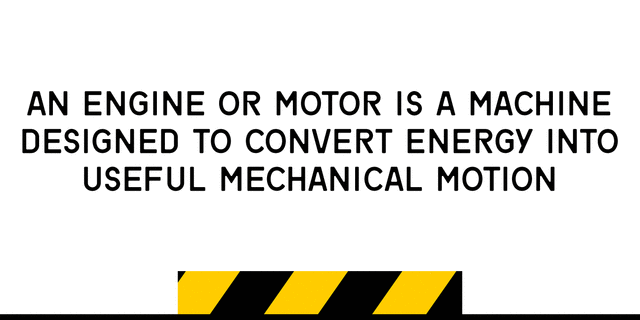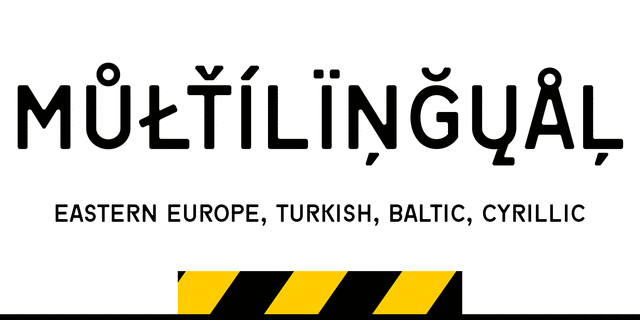
Мотор — акцидентный щрифт, сделан по мотивам букв автомобильных номерных знаков, принятых в России. Разработан Сергеем Ткаченко в 2014 году.
Ассоциации c начертанием Motor 4F BoldКачества и характер:
важный, тяжелый, точный, ровный, убедительный, прямоугольный, стабильный, статичный, простой, нейтральный, прямой, современный, глобализированный, глобалистичный, монотонный, логичный, прагматичный, практичный, твердый, лаконичный, доступный, серьезный, железный, стальной, надежный, уверенный, сильный, устойчивый, автоматический, искусственный, холодный, машинный, инженерный, индустриальный, техногенный, военный, армейский, стандартный, городской, грубый, рабочий, мотивирующий, суровый, железнодорожный
промышленность, техника, станок, код, тара, электростанция, энергетика, армия, оружие, машиностроение, завод, чертеж, конструктор, инженер, автоматика, автомобиль, мотор, ГОСТ, пресс, город, навигация, наука, ремонт, шахта, шахтер, каска, униформа, вагон, авиация, самолет, грузовик, внедорожник, страйкбол, стройка, строительство, обувь, кирпич, дальнобойщик, сталевар, двигатель, технологии, железная дорога, топливо, шоу, телевидение, рабочий, доставка, нефть Стилистика: